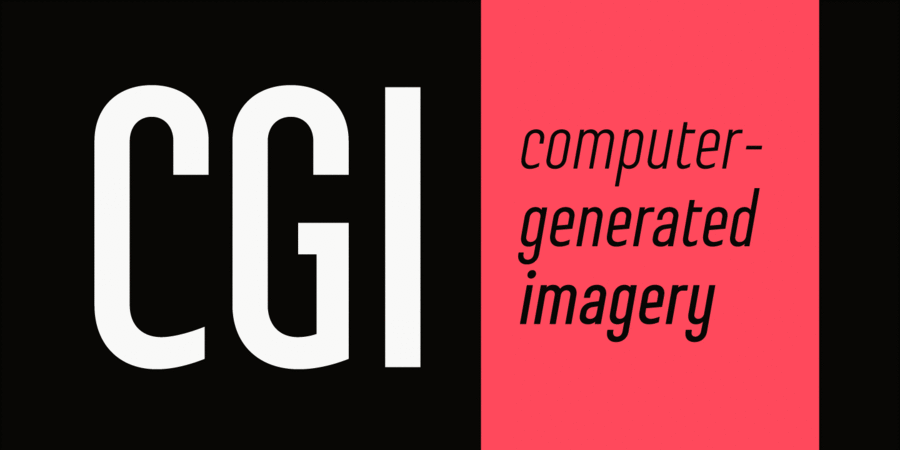
Опис гарнітури StecloЦе напівзакритий вузький акцидентний гротеск з яскраво вираженим технічним характером. Поставляється в 9 вагах від тонкого до наджирного з відповідними нахиленими накресленнями. Steclo має широку мовну підтримку, включно з латинкою та кирилицею. Шрифт розробив Олег Ліщук у 2021 році.
Асоціації з сімейством шрифтів StecloОсобистість і характер гарнітури:
тонкий, стрункий, худий, рівний, високий, міський, вузький, технічний, якісний, точний, чіткий, крихкий, прозорий, сучасний, цікавий, оригінальний, динамічний, гладенький, лаконічний, неоновий, ясний, чистий, серйозний, креслярський, інженерний, твердий, гучний, впевнений, помітний, амбітний, важливий, мотивуючий, переконливий, міцний, сильний, техногенний, залізний, надійний, сталевий, стабільний, автоматичний, індустріальний, практичний, доступний, урбаністичний, крутий, кінематографічний, дорослий, монотонний, стійкий, архітектурний, робочий, відповідальний, рішучий, важкий, суворий, яскравий, виразний, активний, спортивний, сміливий, потужний, гострий
Місто, дієта, креслення, інженер, прилад, хмарочос, кінотеатр, торгівля, магазин, Футбол, фаст фуд, техніка, верстат, інструмент, конструктор, автоматика, промисловість, електростанція, енергетика, авто, автомобіль, кіно, холодильник, паливо, телебачення, шоу, селфі, поліція, політика, новини, будівництво, нерухомість, завод, архітектура, робочий, бар, спорт, блокбастер, екскаватор, тренажери, машинобудування, металургія Гарнітура асоціюється з віком: